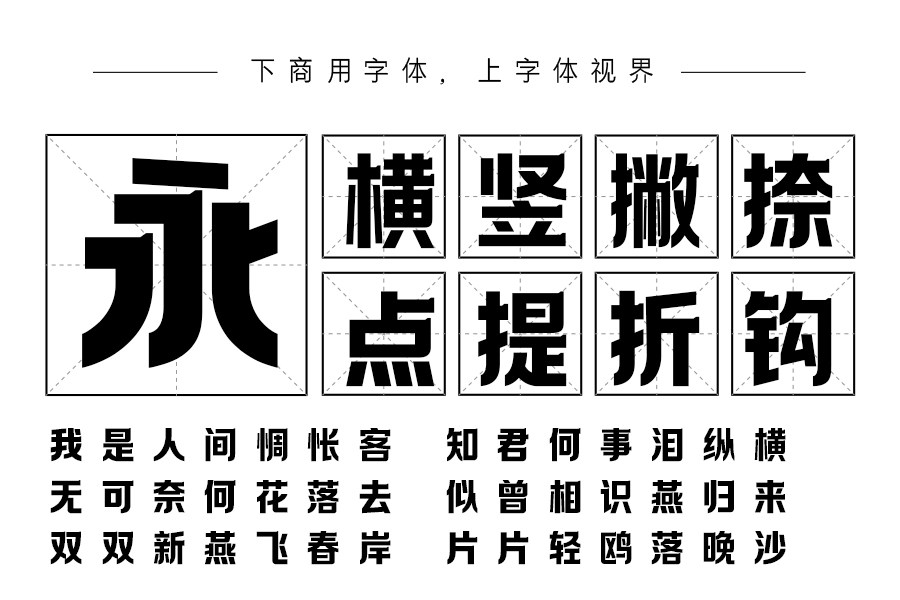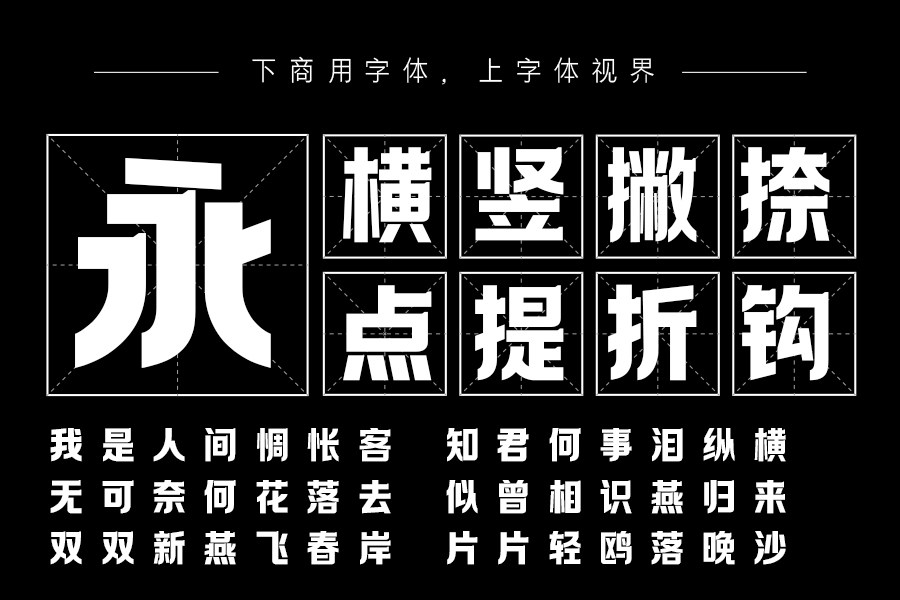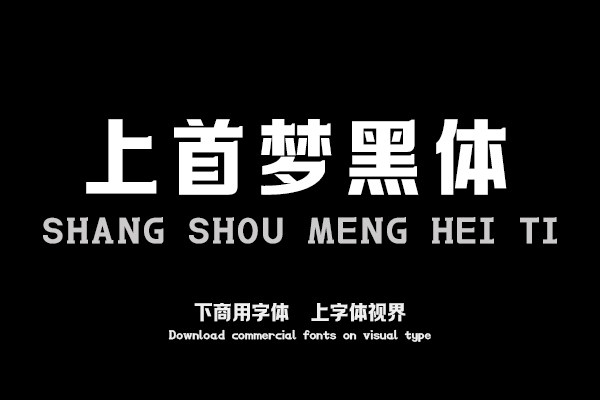
上首梦黑体,简体中文约6763字,字体横笔右上角有突出的小梯形,使字体显得更具特点,撇捺利用流畅的曲线,使字体刚中带柔,在笔画连接处进行了倒角处理是这套字的一大......购买须知:“下载服务费”与“字体VIP”所获得字体 仅用于个人非商用, 商用请联系付费授权。本字体为电脑用字,手机没有root权限不支持直接手机换字(手机如何root,请自行百度搜索教程)。购买前请先 了解清楚后再付款 ,字体为虚拟产品无法回收 一旦购买不支持退款。